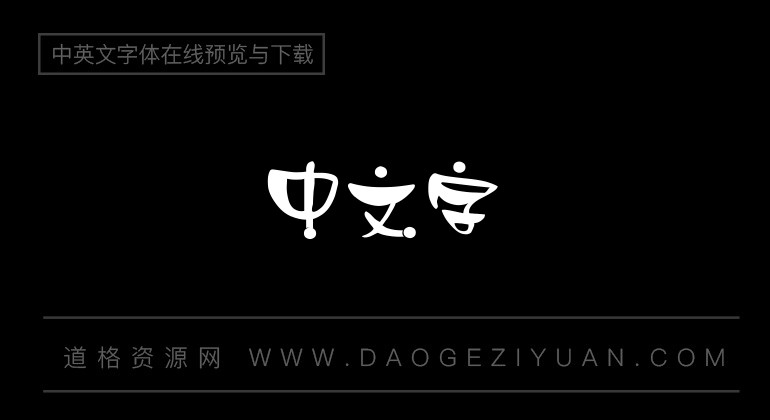
金梅浪漫豆豆字体是一种特殊的汉字字体,它采用了类似于梅花的细节,给人以浪漫的感觉。它的特点是字体的笔画细腻,线条流畅,而且还具有一定的空间感,可以很好地表达情感。金梅浪漫豆豆字体可以用于排版,也可以用于文字装饰,可以增加文字的艺术感。文件名:jinmeilangmandoudou.ttf
金梅浪漫豆豆字体是一款非常不错的手写艺术字体,具有很好的视觉感,适合于文化类的宣传设计、商业类品牌的广告和产品包装设计以及个性化文字排版等较多场景。